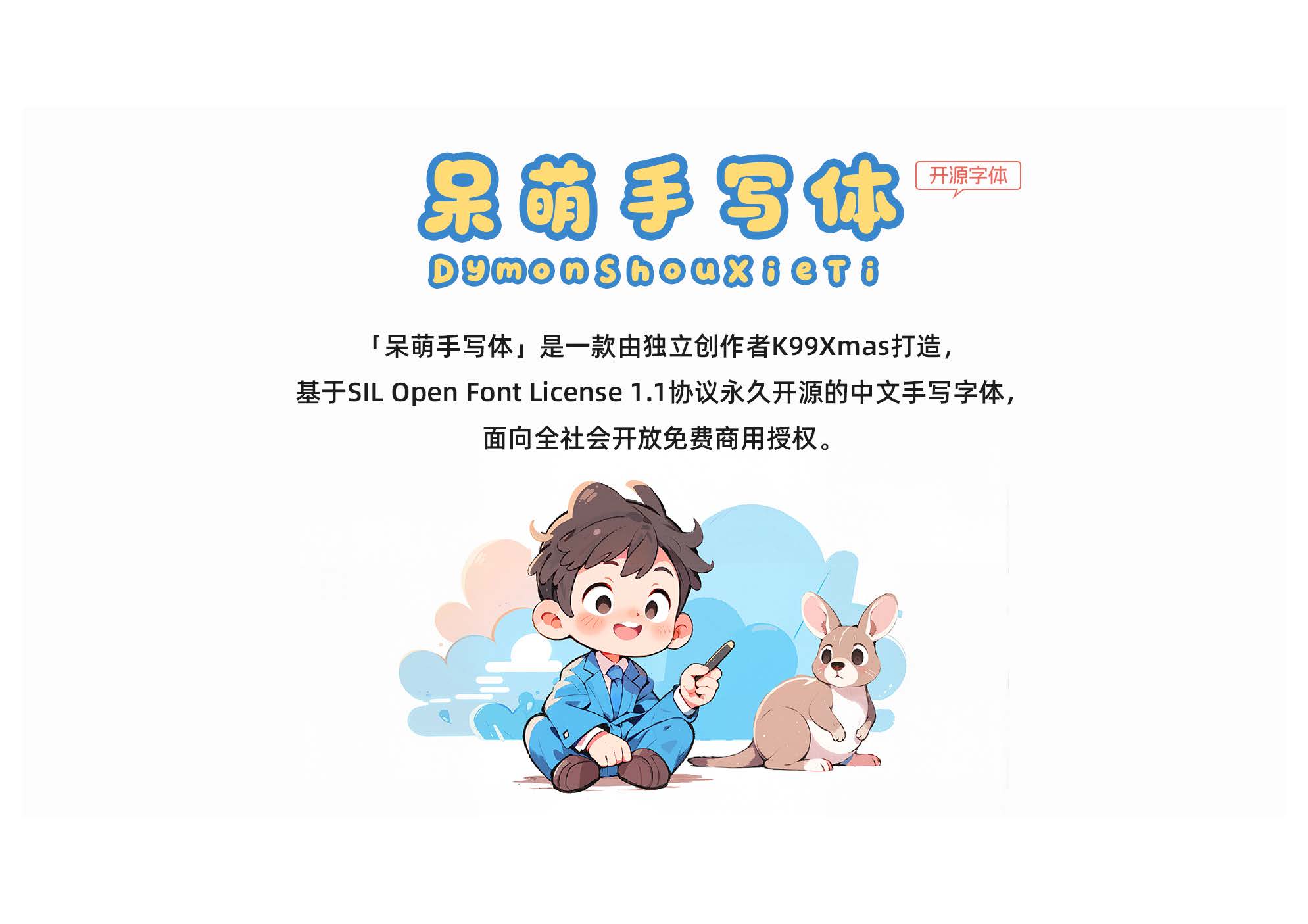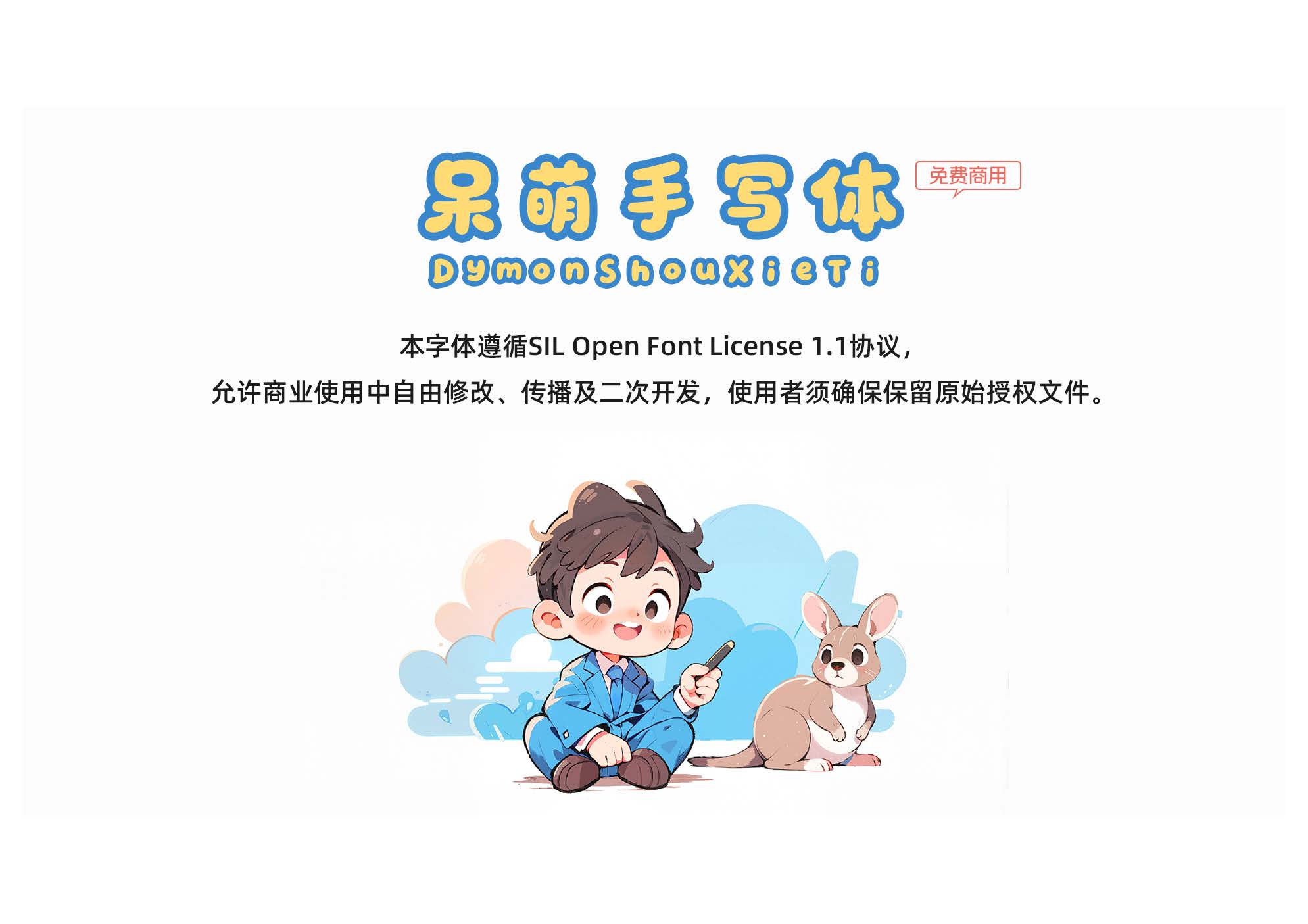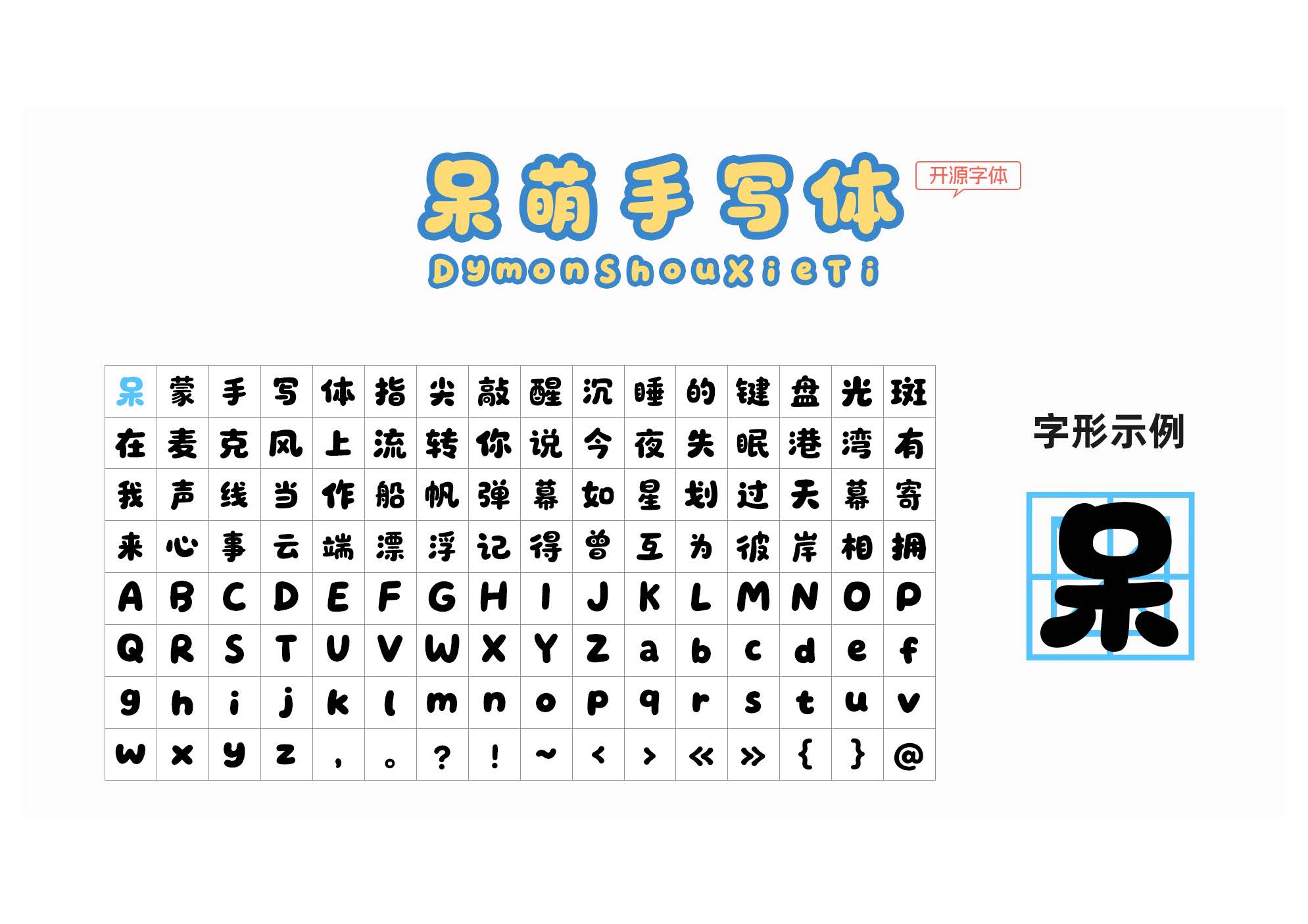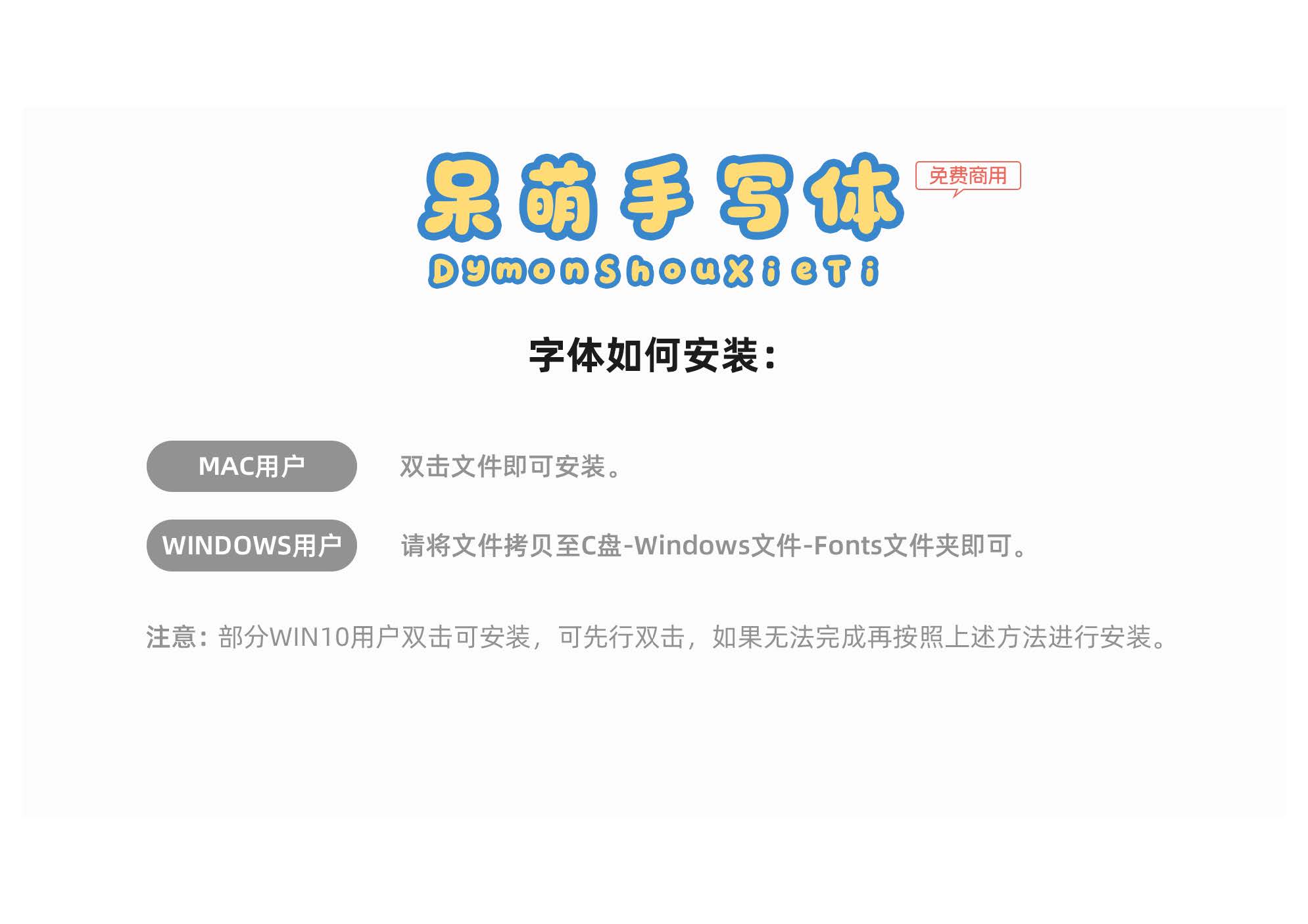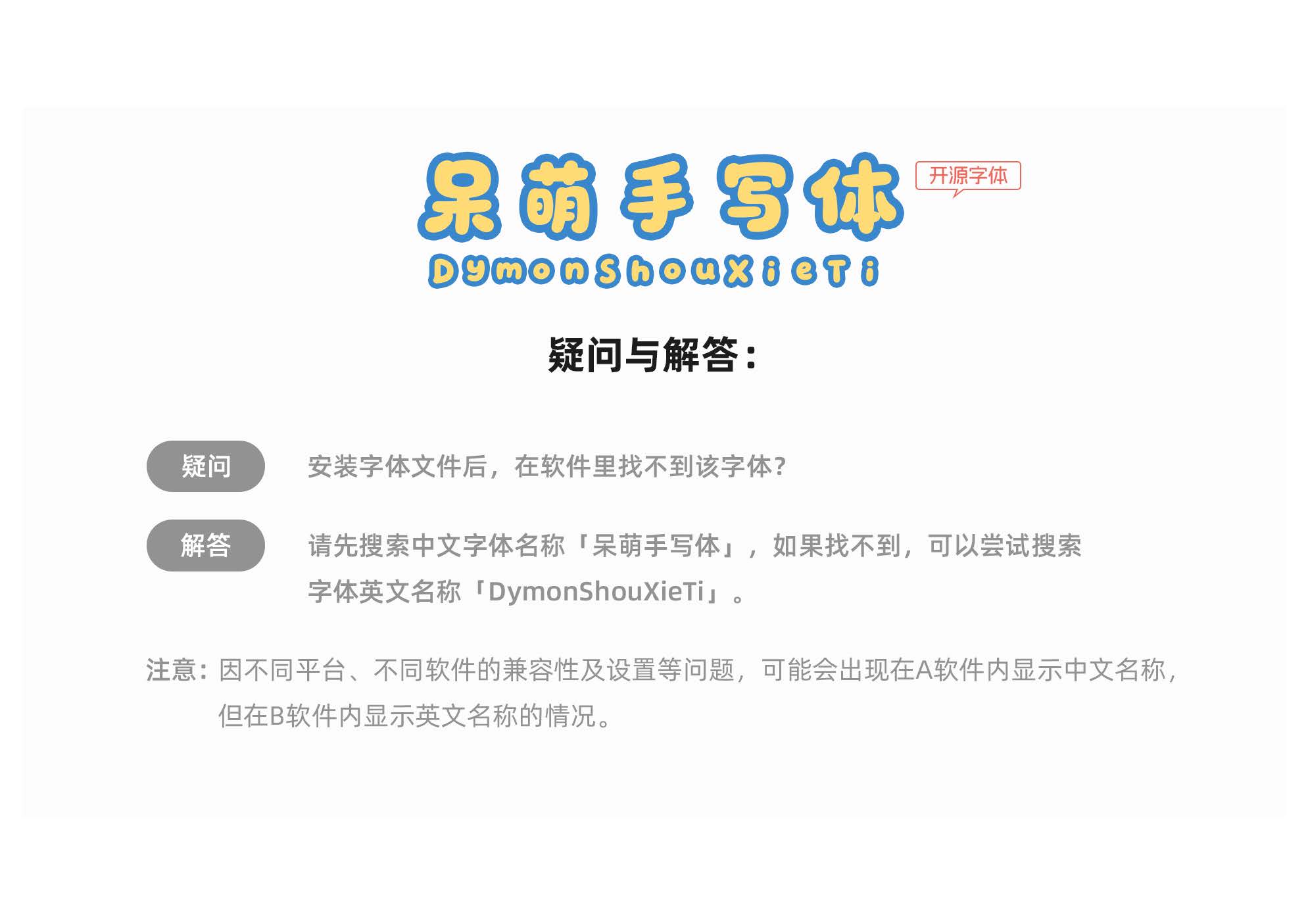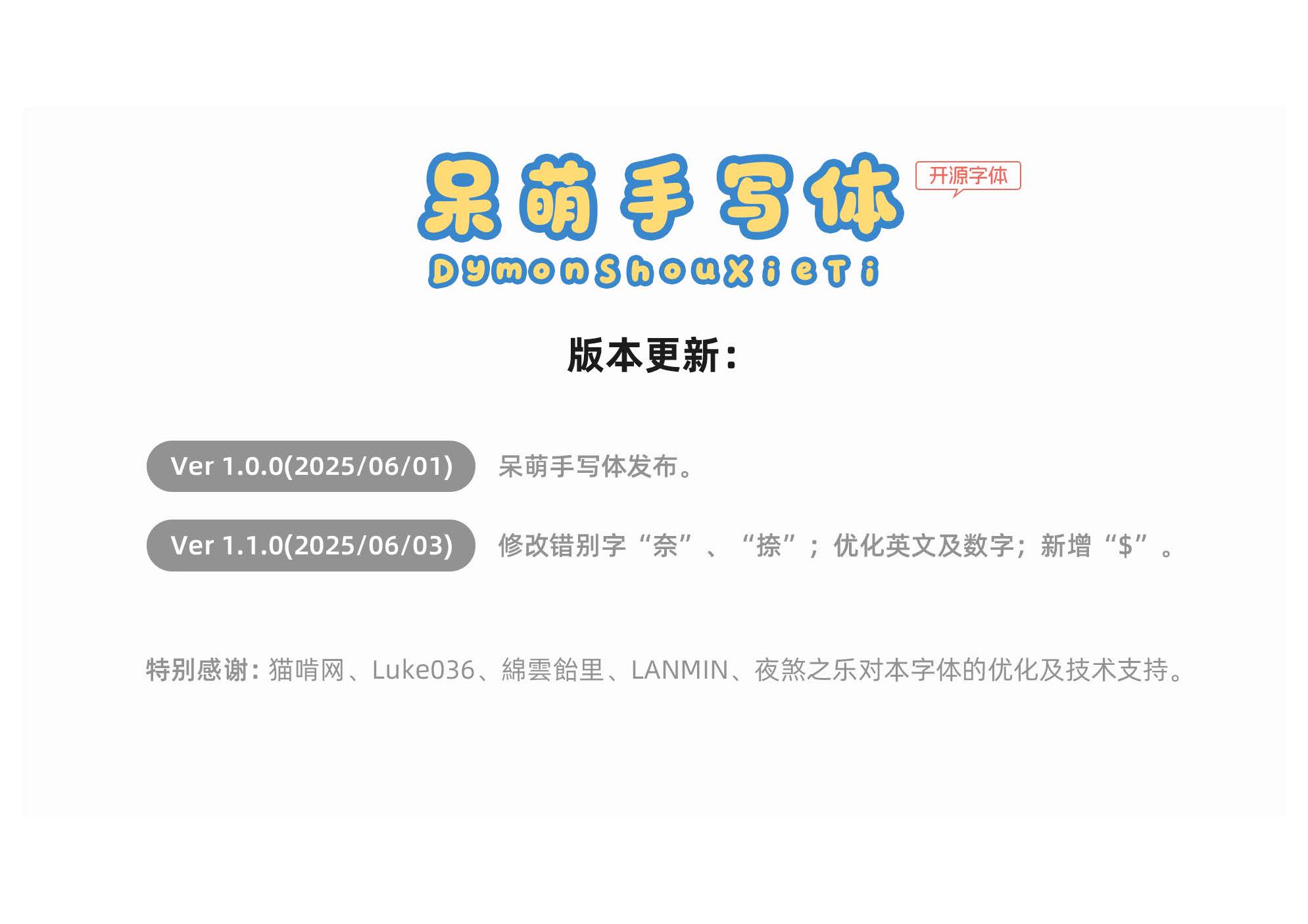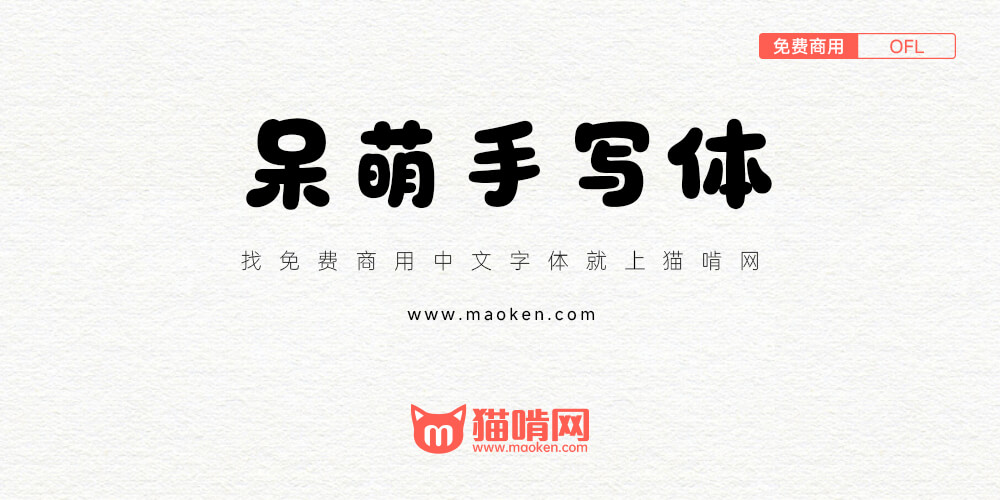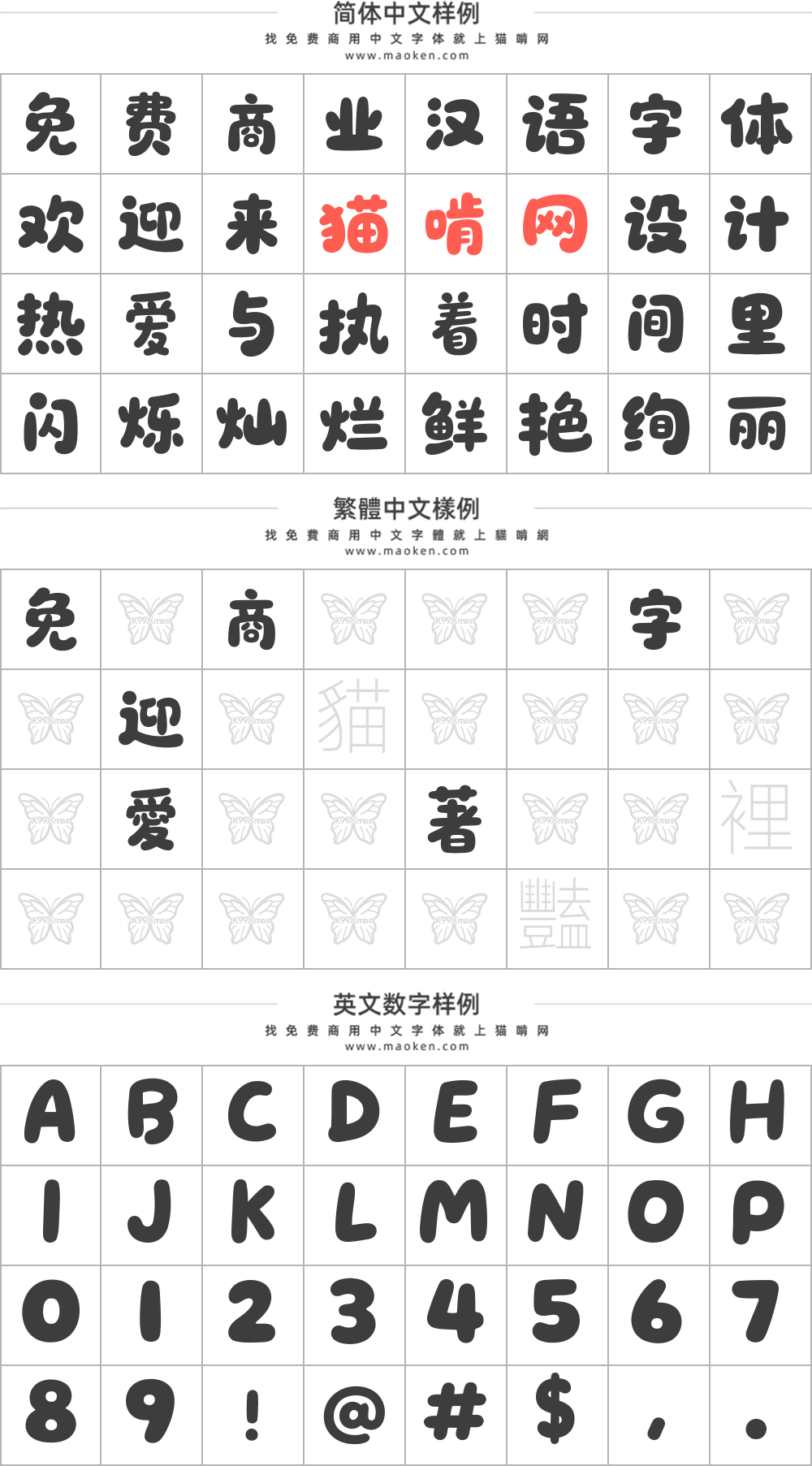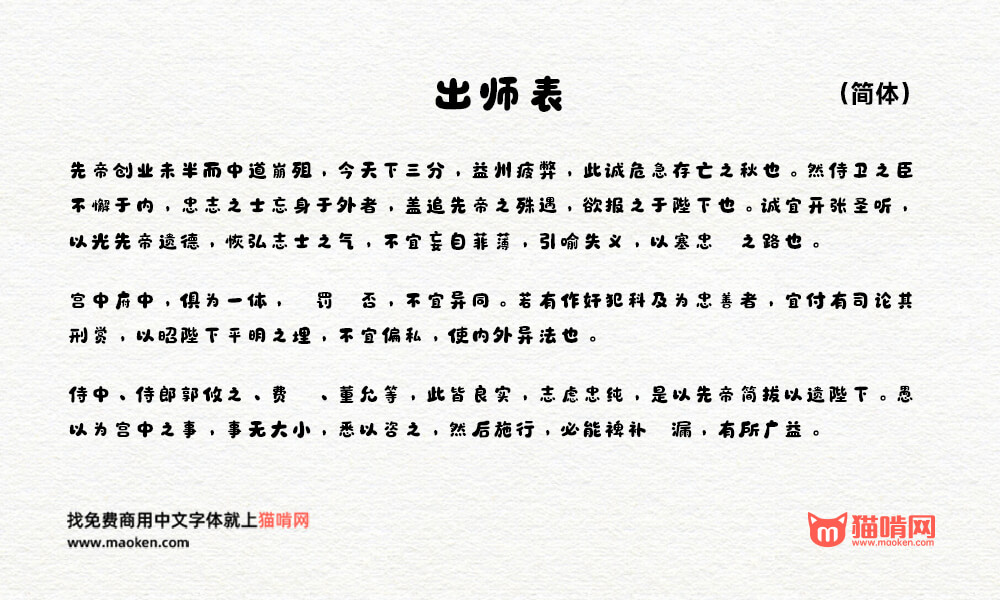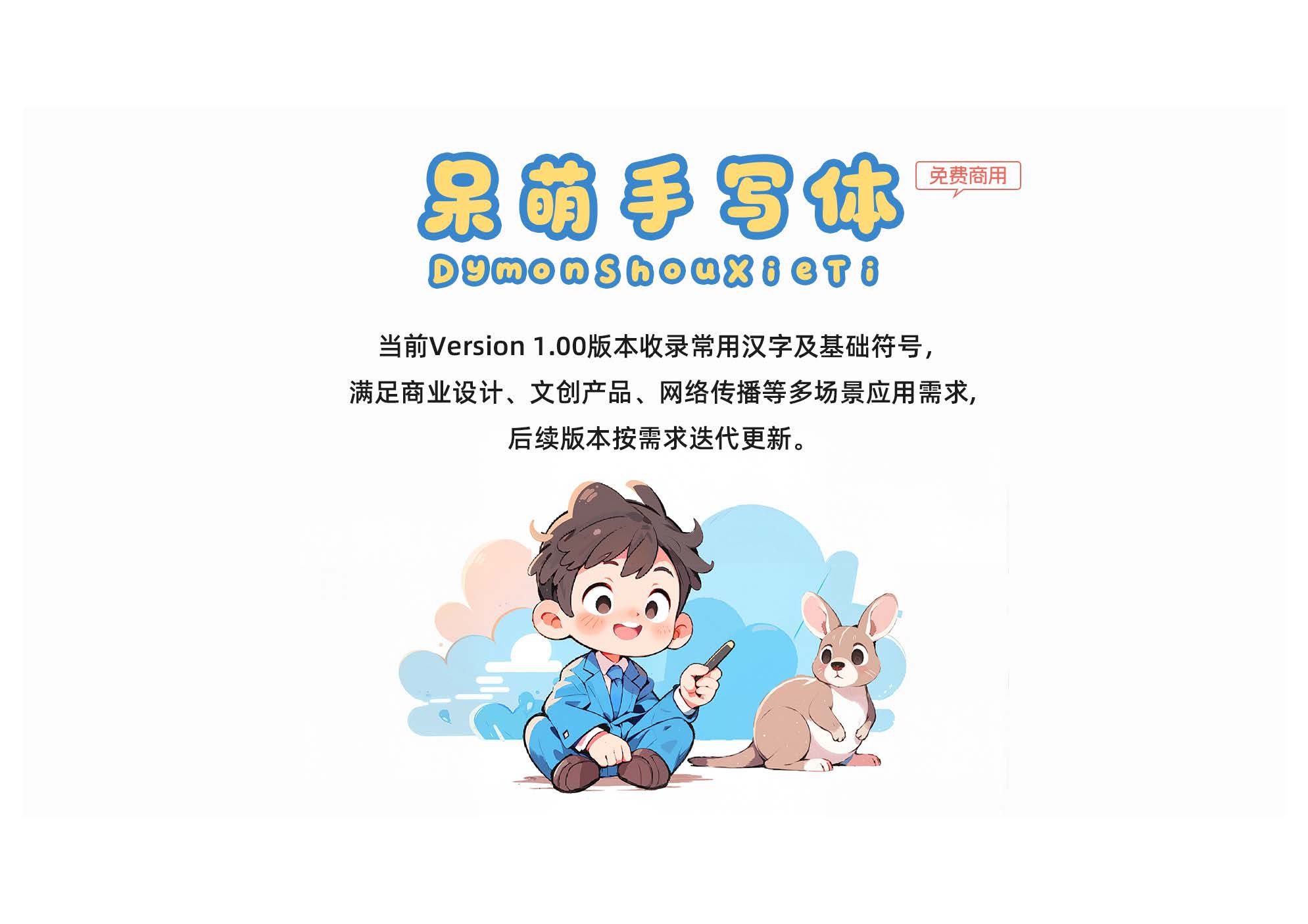
| 字体作者:K99Xmas (中国大陆) | 字体字重:1个 |
当前Version 1.00版本收录常用汉字及基础符号,满足商业设计、文创产品、网络传播等多场景应用需求,后续版本按需迭代更新。
这款字体保留自然书写的温度感:圆润造型与稚拙的笔划结构相映成趣,通过灵动的连笔转折与适度的墨迹留痕,营造出充满童真的视觉韵律。每个字符曲线Q弹,既保持文字识别性,又赋予版面独特的治愈系氛围。